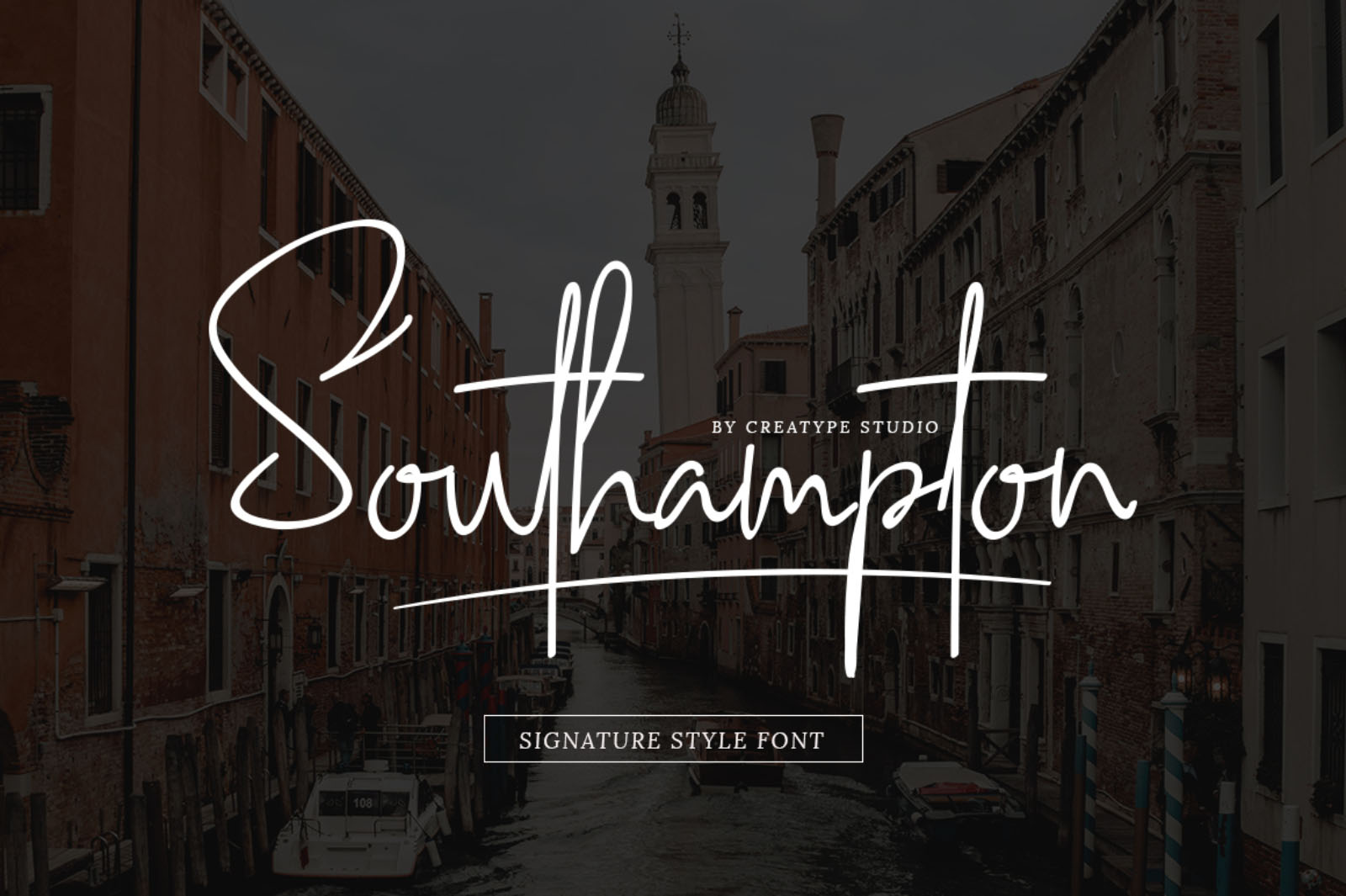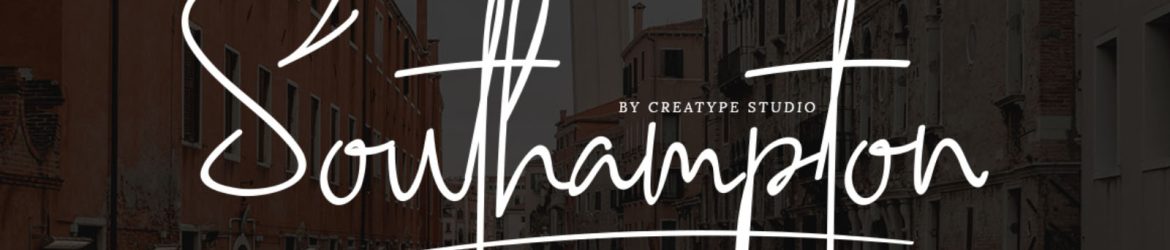
Southampton Handwritten Free Font – Download Grátis
A Southampton Handwritten Free Font é uma escolha perfeita para aqueles que desejam dar um toque único e pessoal a seus projetos de design. Com seu estilo elegante e moderno, esta fonte escrita a mão apresenta uma letra que transmite a autenticidade de uma letra escrita à mão, fazendo-a perfeita para variados usos. Seja para criar logos e marcas, cartões de convite, embalagens de produtos, materiais de publicidade ou mesmo um design de etiqueta, a Southampton traz um brilho especial ao seu projeto. Não importa qual seja o propósito do seu design, a fonte Southampton garantirá um efeito autêntico e encantador. Seja ele um post em redes sociais, um anúncio de produto ou até mesmo uma etiqueta de produto, a Southampton pode transformar suas ideias em realidade, dando-lhe um design único e verdadeiramente autêntico.